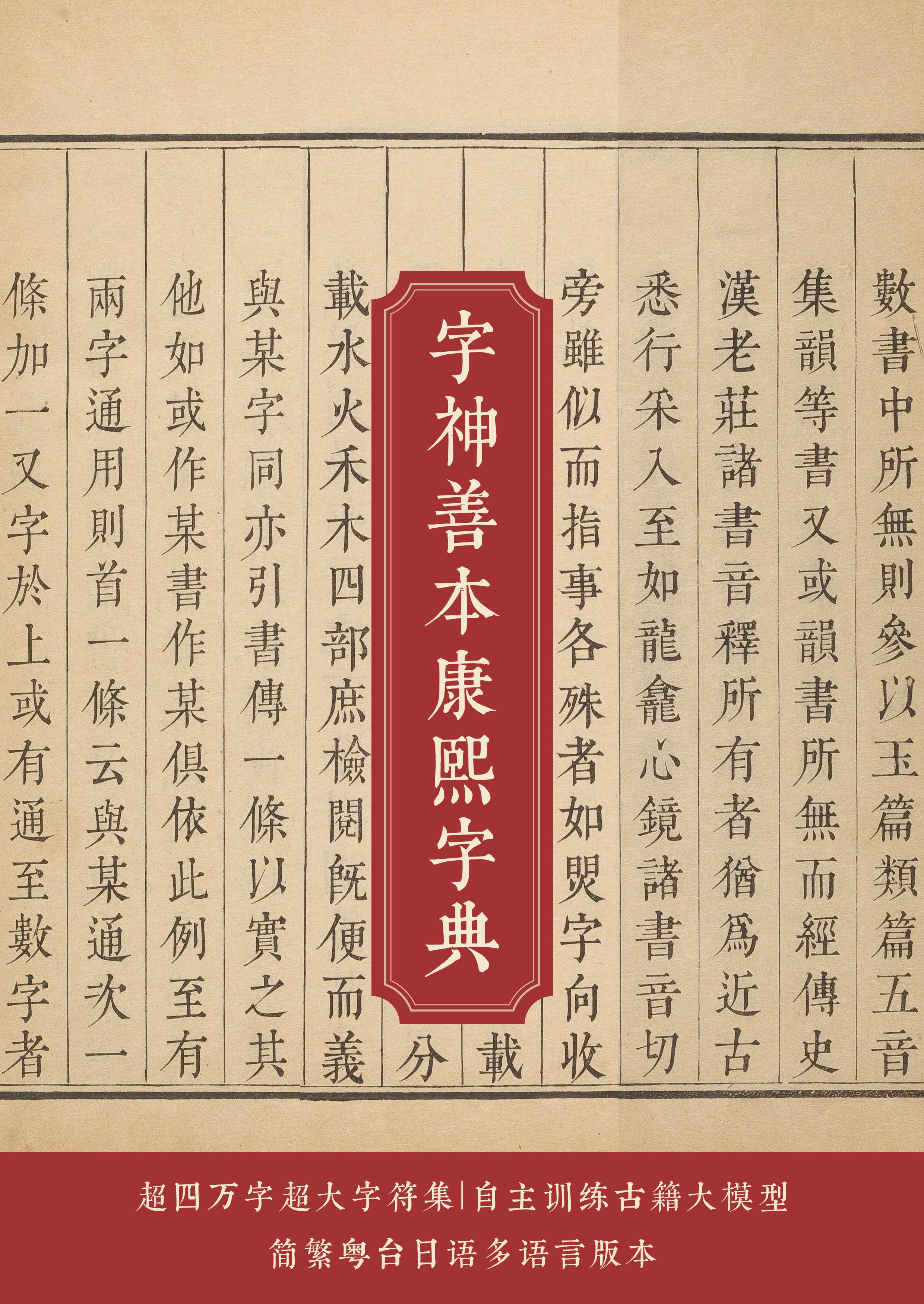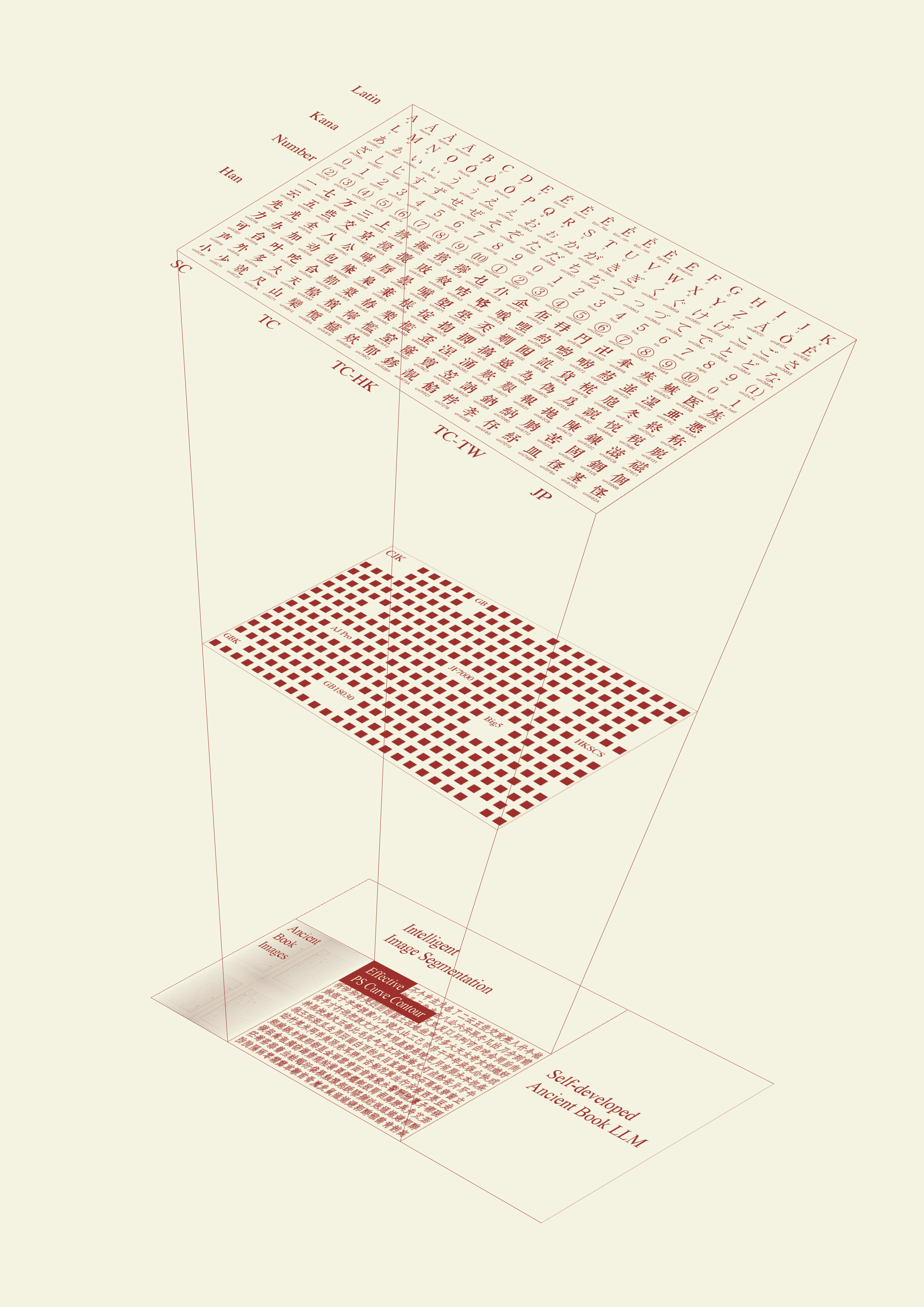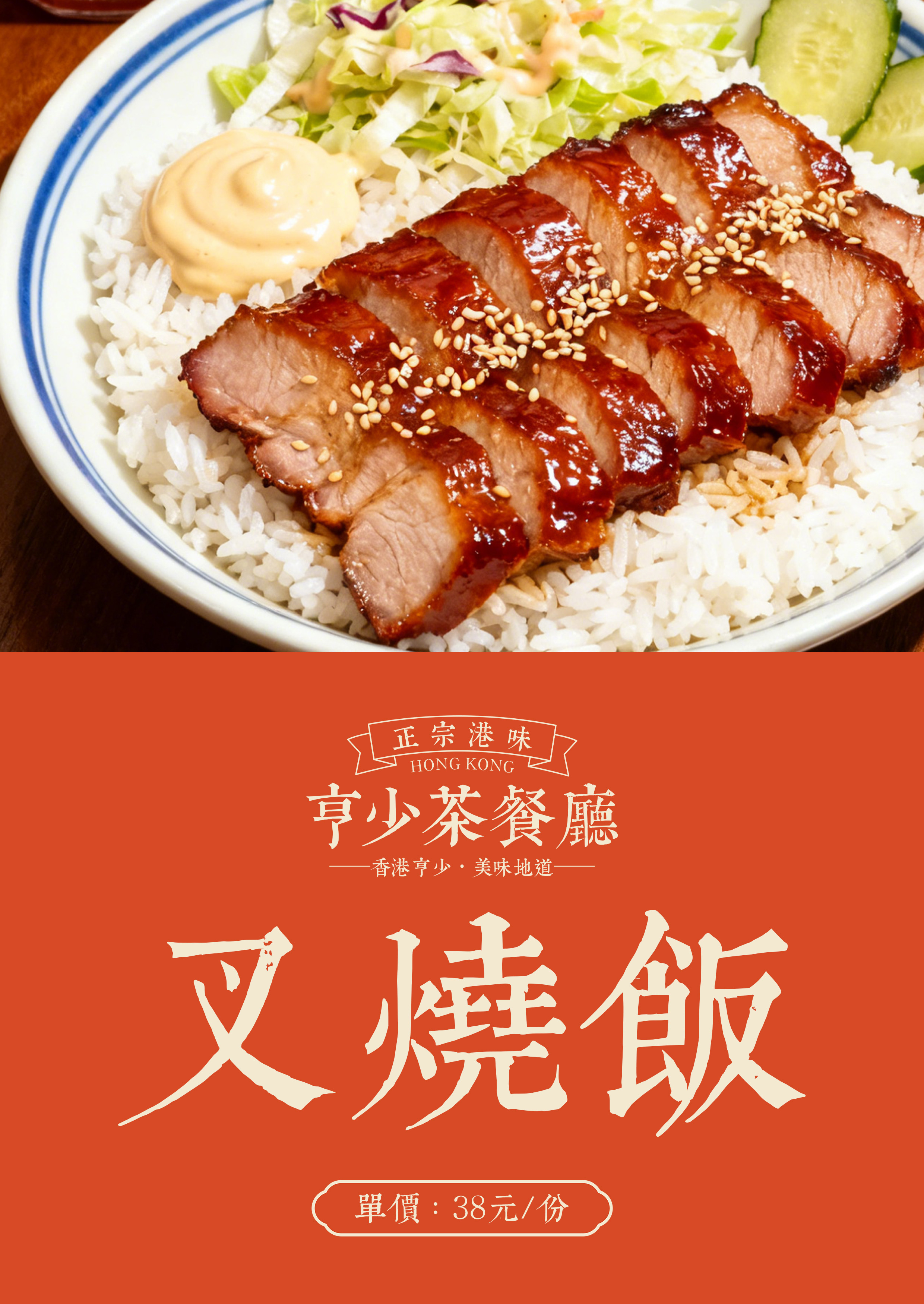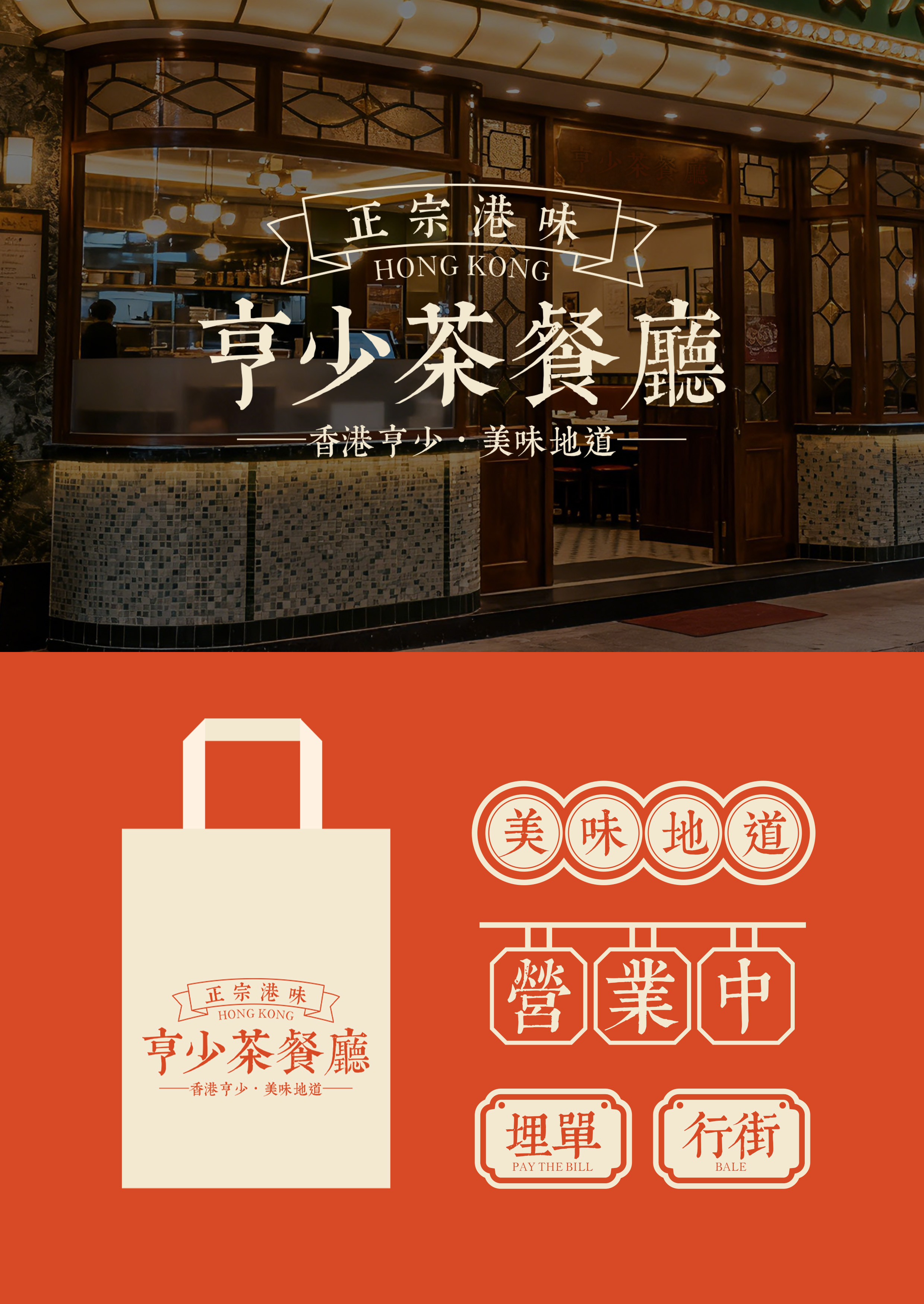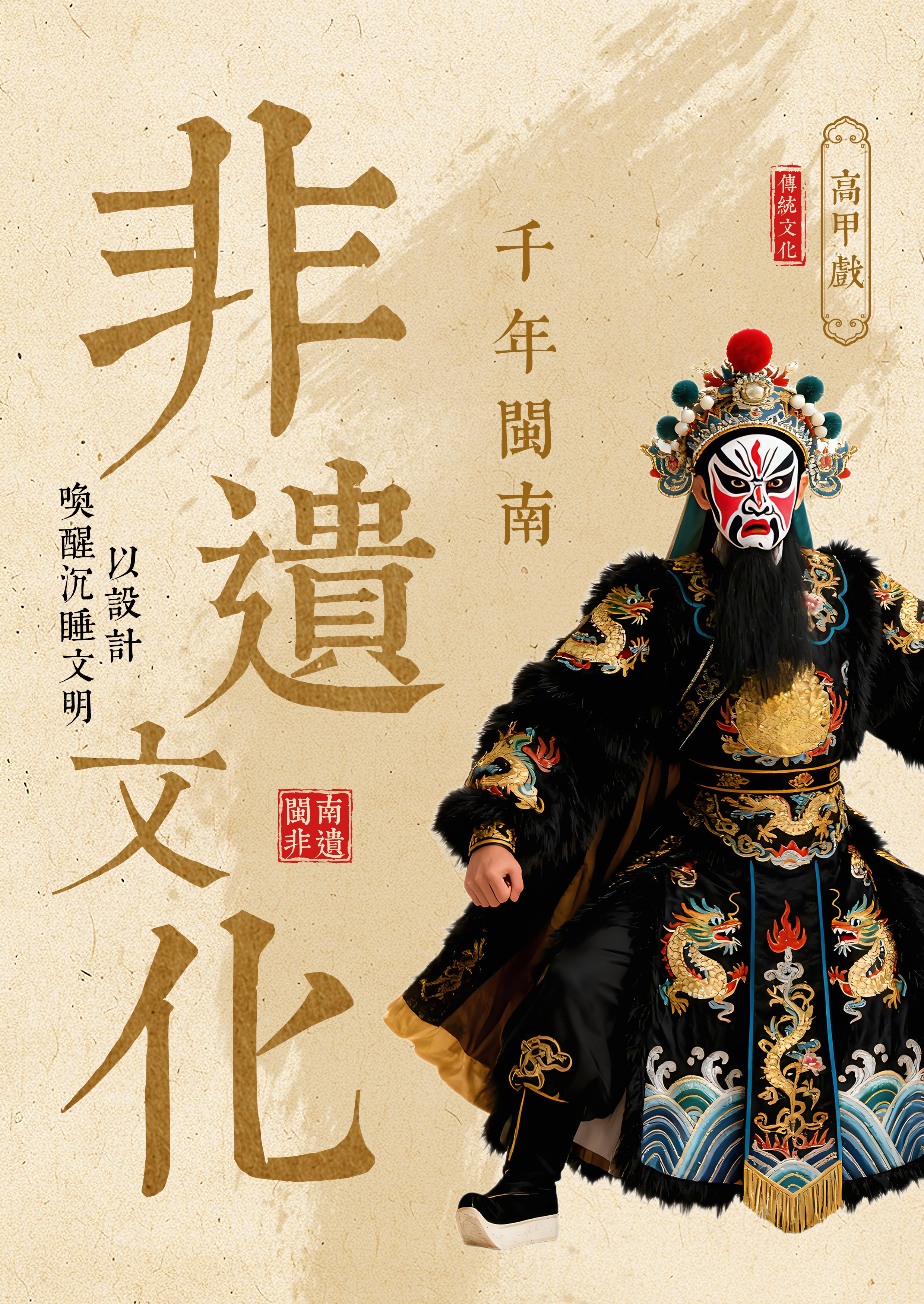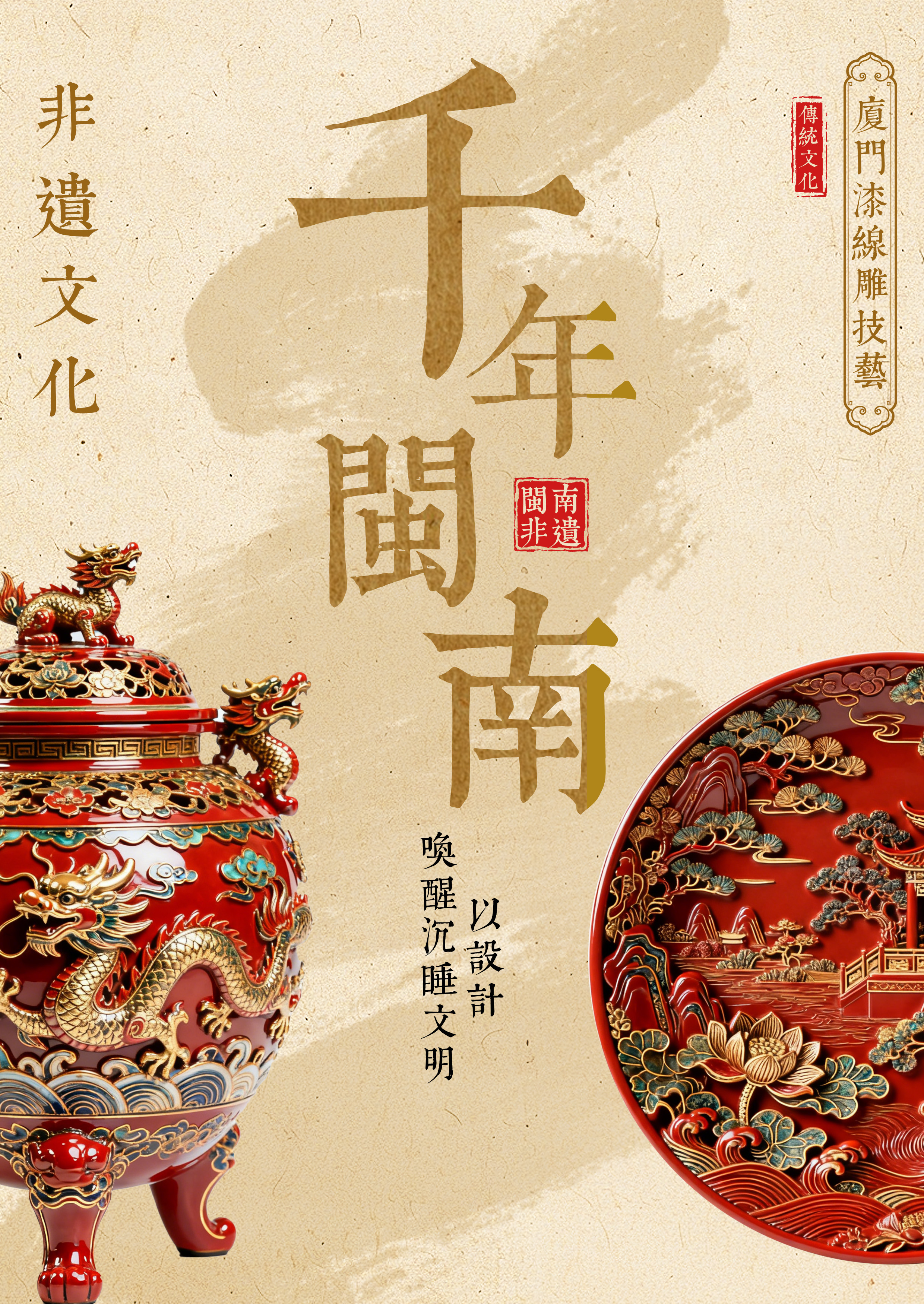
字神善本康熙字典简繁
《康熙字典》的字型源于武英殿精刻典籍之风范。内府刊本多以庄重宋体字刻印排版,其典籍以书品端严、版印精审而传誉后世。而《康熙字典》最是典范,其字形外方内长,横轻竖重,笔画起收处带刀刻棱角,整齐中更显端庄秀雅之美。“字神善本康熙字典B5-HK”还原自康熙五十五年内府刊本的《康熙字典》,收录五大码以及常用香港粤语字符集。字型的复刻严谨,再现工匠刀刻精劲之力,笔刀相契刚柔相济。复刻中留存的原版笔画细节,在字里行间深蕴历史沧桑之味,给人以古朴真切之美。适合文化宣传、电商设计、书籍封面、品牌视觉、文创周边等应用场景。